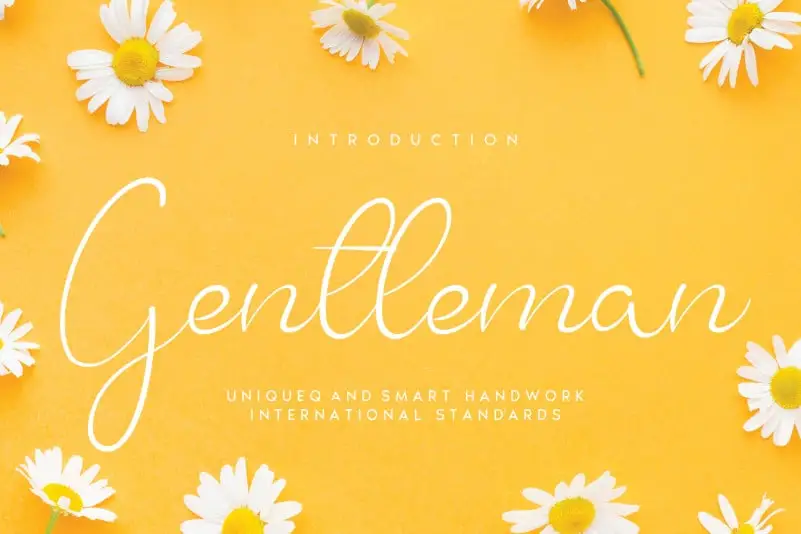
Gentleman Script Font – Download Grátis
A Gentleman Script Font é uma elegante escolha para designers que buscam um estilo autêntico e criativo para seus projetos, com um toque suave que transmite confiabilidade sem ser formal. Desenvolvida pelo designer andikastudio, essa fonte escrita a mão oferece uma experiência única de design. Perfeita para aplicar em trabalhos como cartões de aniversário, camisetas personalizadas, ou qualquer outro projeto onde um toque autêntico pode fazer toda a diferença. Com seu traço delicado e rica textura, a Gentleman Script Font traz uma sensação de familiaridade e conforto que encoraja seus usuários a relaxarem e desfrutarem do processo criativo. Esta fonte escrita a mão não apenas oferece um visual único, mas também uma experiência de usabilidade fluida. Em um mundo cada vez mais digitalizado, encontrar algo autêntico como essa fonte pode fazer uma grande diferença em sua identidade gráfica e personalização. Com sua graça suave e texto trabalhado, a Gentleman Script Font é perfeita para criar designers que desejam transmitir um toque de personalidade em seus projetos. Seja você um designer digital ou impresso, essa fonte escrita a mão é uma ótima opção para se juntar ao andikastudio e experienciar o verdadeiro sentido de uma criação autêntica.